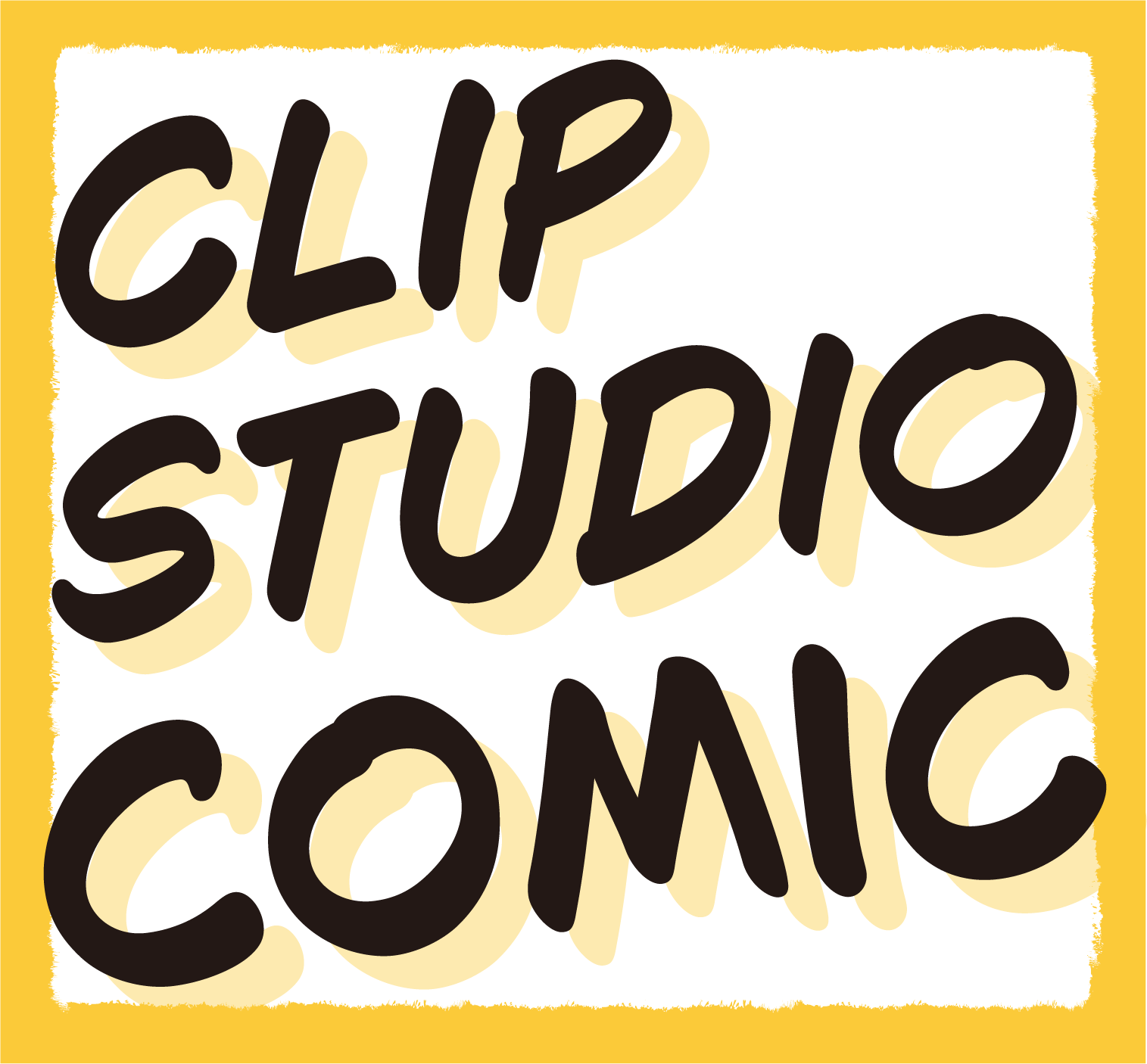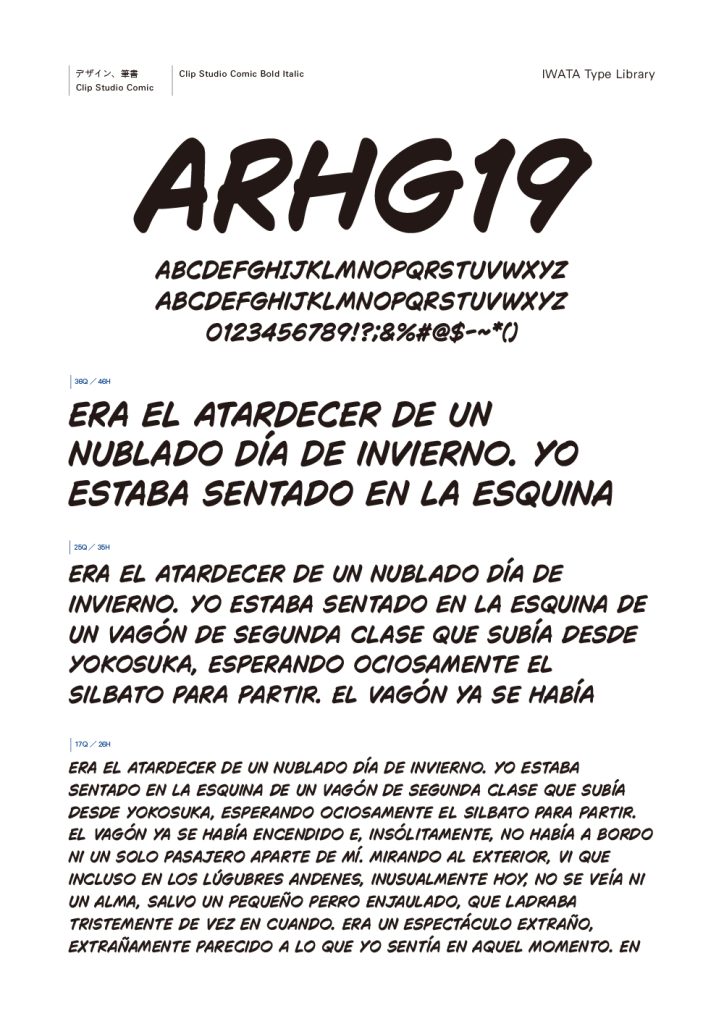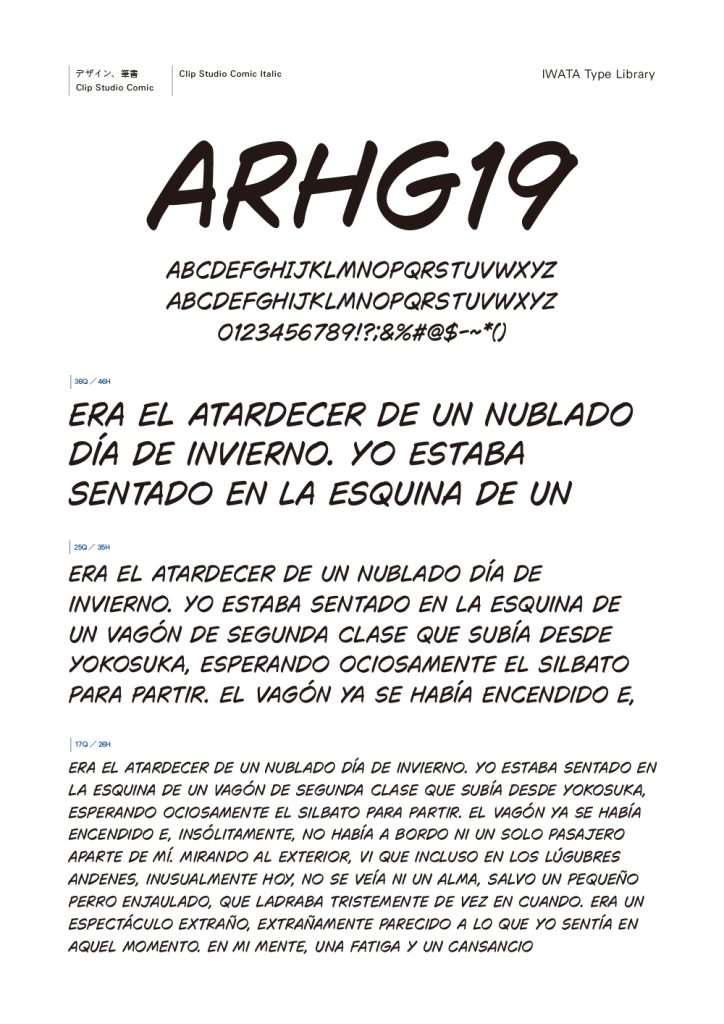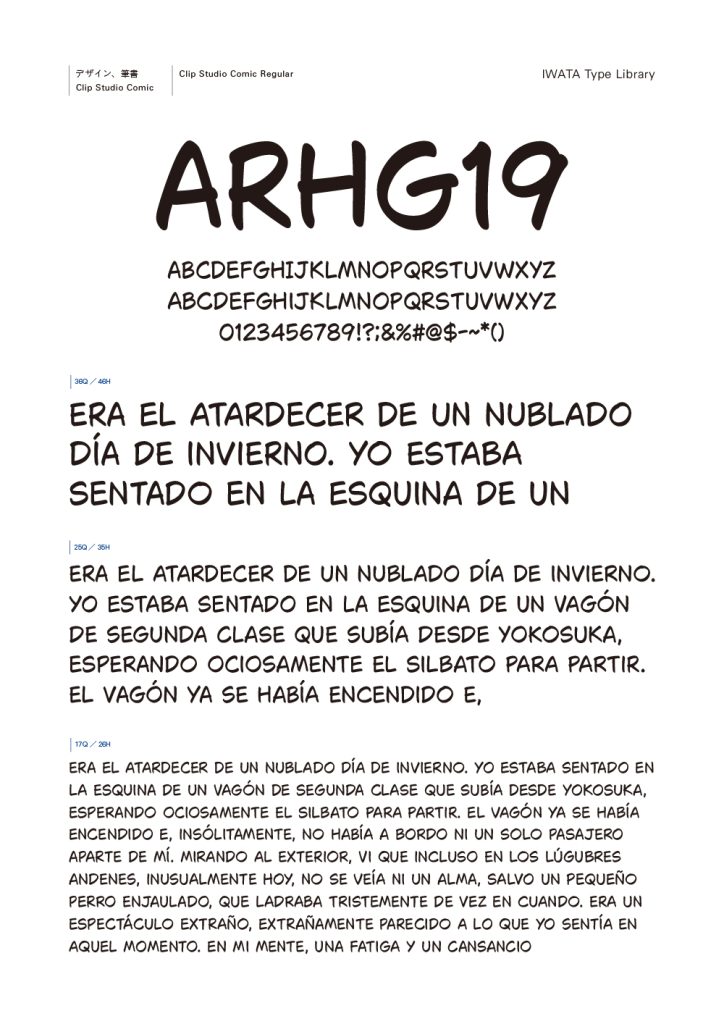
Clip Studio Comic
CLIP STUDIO PAINTのブラシツールを使って書かれたラフスケッチを元に開発された、手書き風の欧文書体です。 文字ごとに線の強弱や高さの揺らぎを取り入れ、手書き特有の自然さや親しみやすさを表現。1文字に4つの字形を持たせてランダムに切り替える仕様や、欧米ユーザーの声を反映した文脈に応じて大文字「I」をCrossbar I(上下に横線付き)へ自動変換する機能など、リアルな表現を追求しています。